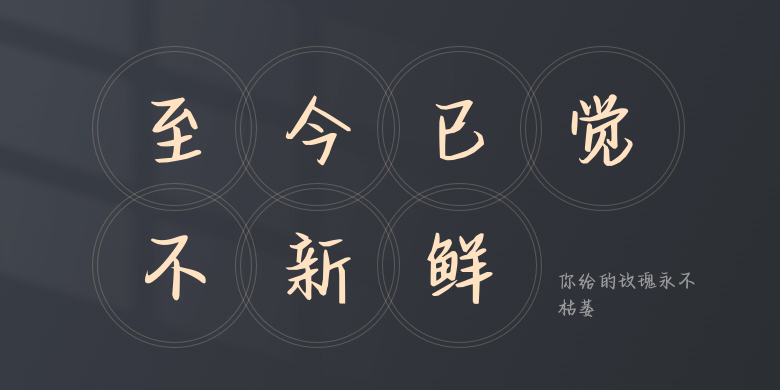
你给的玫瑰永不枯萎
你给的玫瑰永不枯萎,这款字体结构工整、笔画清晰,兼顾美观与易读性,适用于标题、正文、海报、包装、LOGO 等多种场景。字形优雅稳定,风格百搭耐看,适配日常排版与创意设计,让文字呈现更舒适、更具质感。你给的玫瑰永不枯萎一笔一画,皆是细节,以均衡的比例、流畅的线条打造舒适视觉体验,字形端正大气,风格简约现代。无论是商业设计、品牌宣传还是日常排版,都能轻松驾驭,让文字更有格调与力量。你给的玫瑰永不枯萎字体下载。